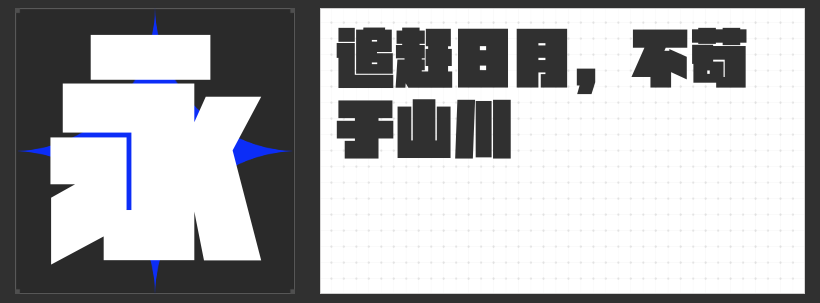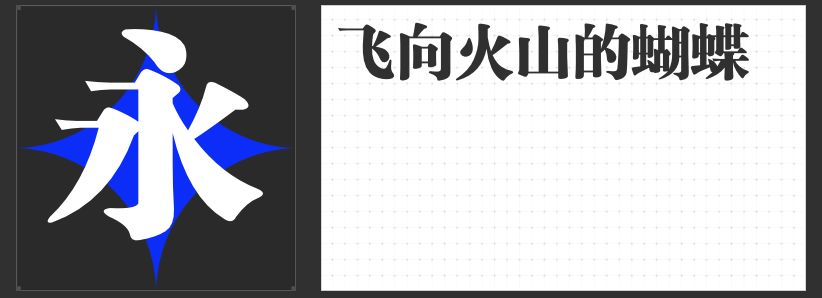
经典风设计字体优选:四款励字佳作诠释永恒魅力
在经典风格的设计领域,字体是传递韵味与格调的关键元素。合适的字体能为作品赋予深厚的文化底蕴与独特的艺术气质。以下四款字体,各具特色,是经典风设计的理想之选。
以其方正字型和独特笔画设计脱颖而出。中宫较大、重心适中,让字体整体稳定而协调。全部直线笔画,横平竖直、棱角分明,尽显简约之美。起笔和收笔的平切处理,内部几何空间的均匀分布,赋予了字体强烈的秩序感。部分钩笔画的去钩处理,以及撇、捺、点的竖直运用,营造出强烈的镜像视觉效果,使字体在经典中透露出前卫与个性,适合追求独特经典风格的设计。
二、励字综艺简繁
笔划粗壮,力求将空间填满,展现出饱满的视觉冲击力。拐弯处圆润、方正的处理,既美观又富有变化。笔画虽粗,但横平竖直,规矩中不失活泼,艺术性十足。这种字体在经典风格中融入了时尚元素,既保留了传统的庄重感,又增添了现代的灵动气息,为经典设计带来别样的活力。
三、励字粗圆简繁
字面较大,结构方正饱满,给人一种端庄大气之感。笔形柔和,笔画较粗,端正大方的形态仿佛在诉说着经典的故事。它没有过多复杂的装饰,却以简洁的线条和圆润的笔触,展现出经典的优雅与从容,是营造经典氛围的得力助手。
四、励字新粗宋简
在保留宋体字基本特点的基础上大胆创新。字形横细竖粗,末端装饰部分增添了精致感。点、撇、捺、钩等笔画的尖端设计,使字体更具灵动性。字型扁方,打破传统结体方式,为经典风格注入了新的活力与变化,让经典设计在传承中焕发出新的光彩。